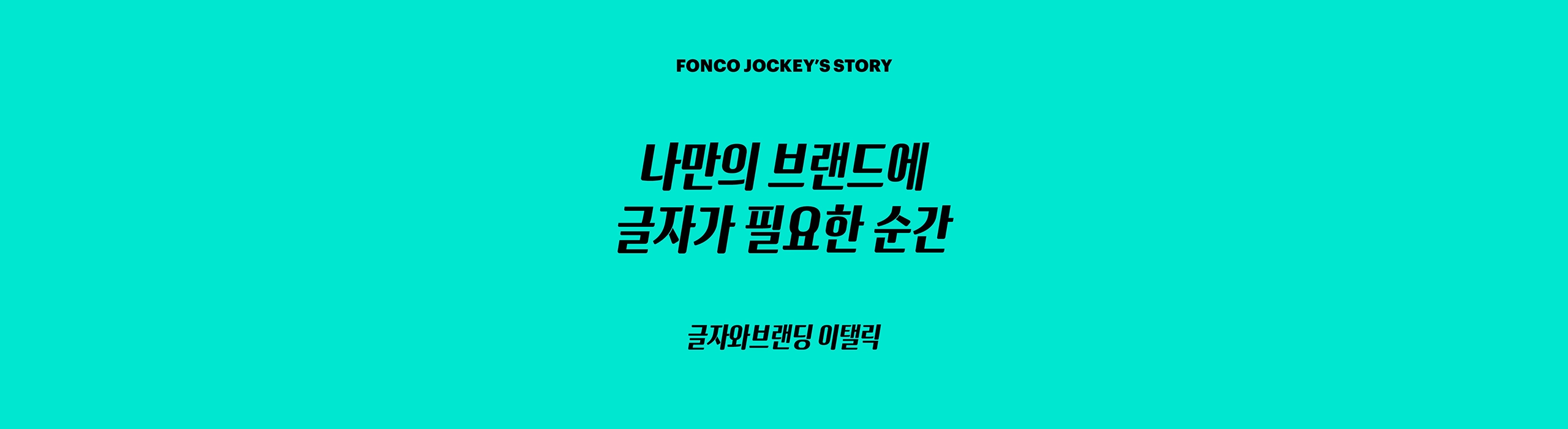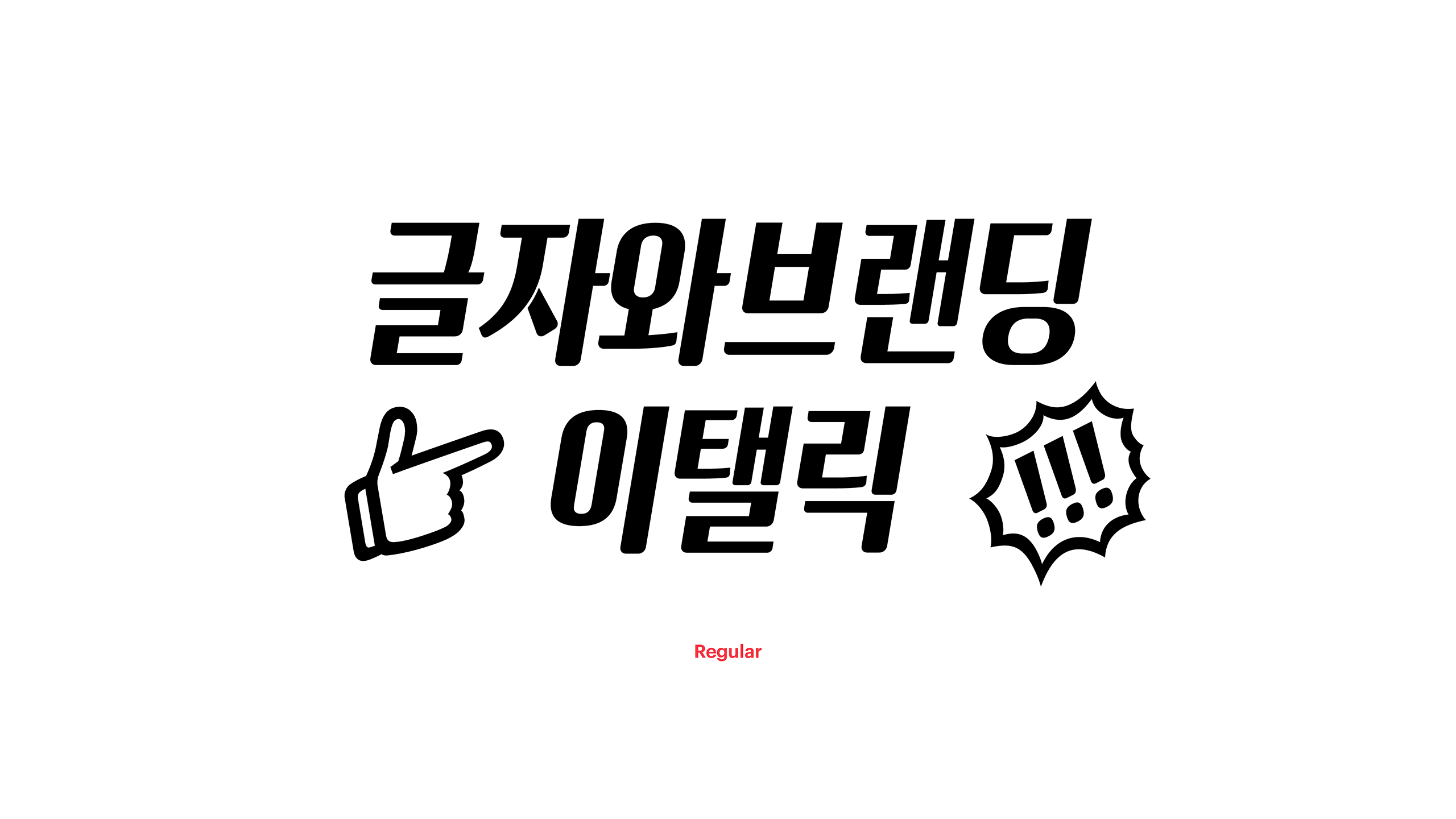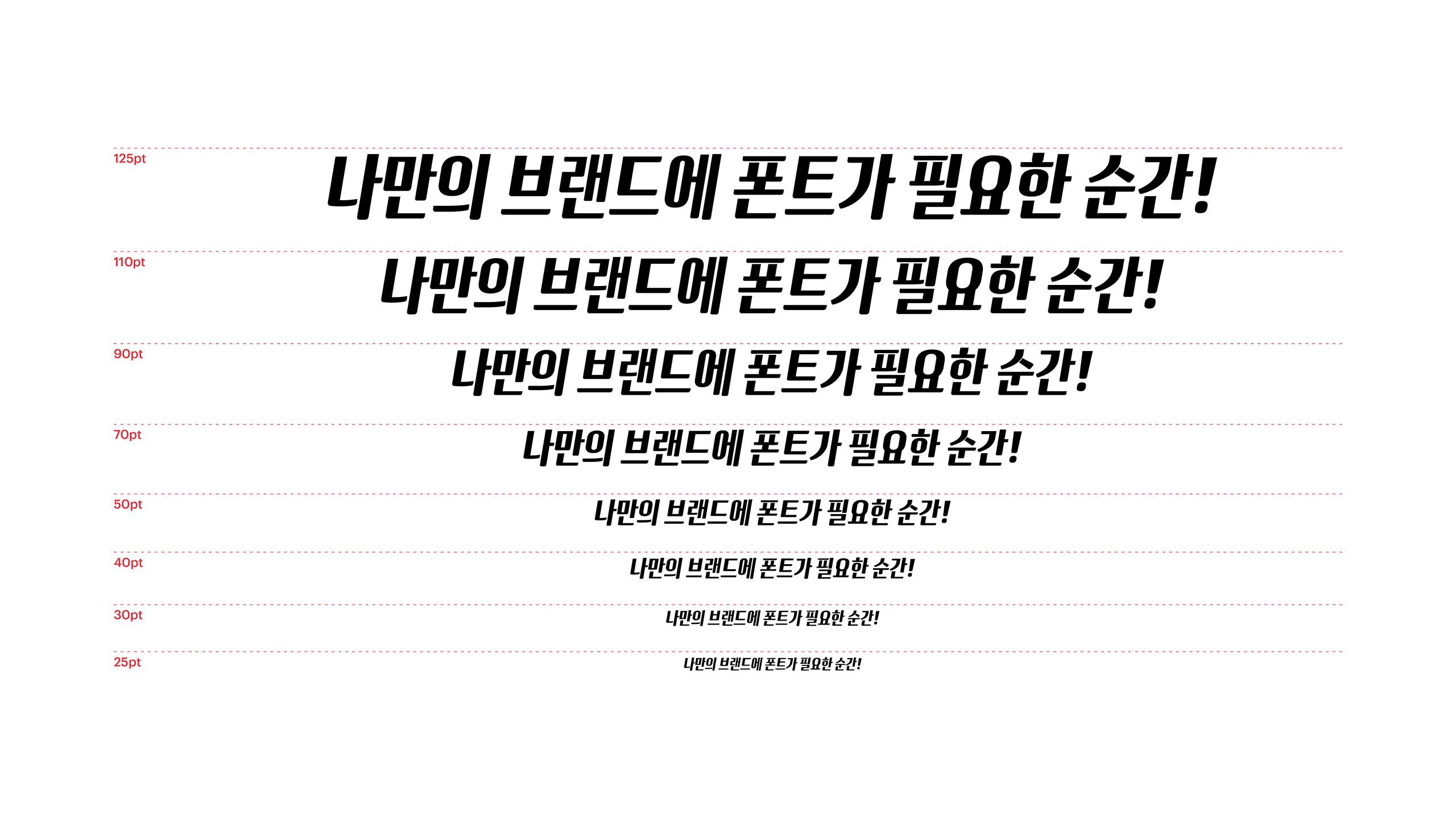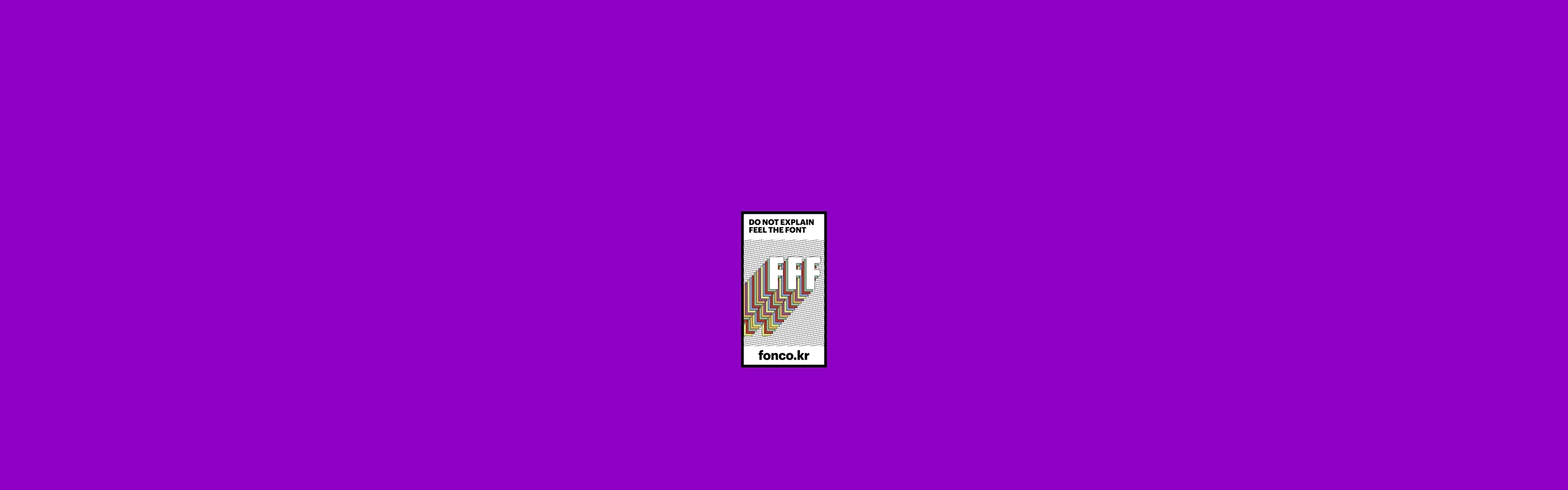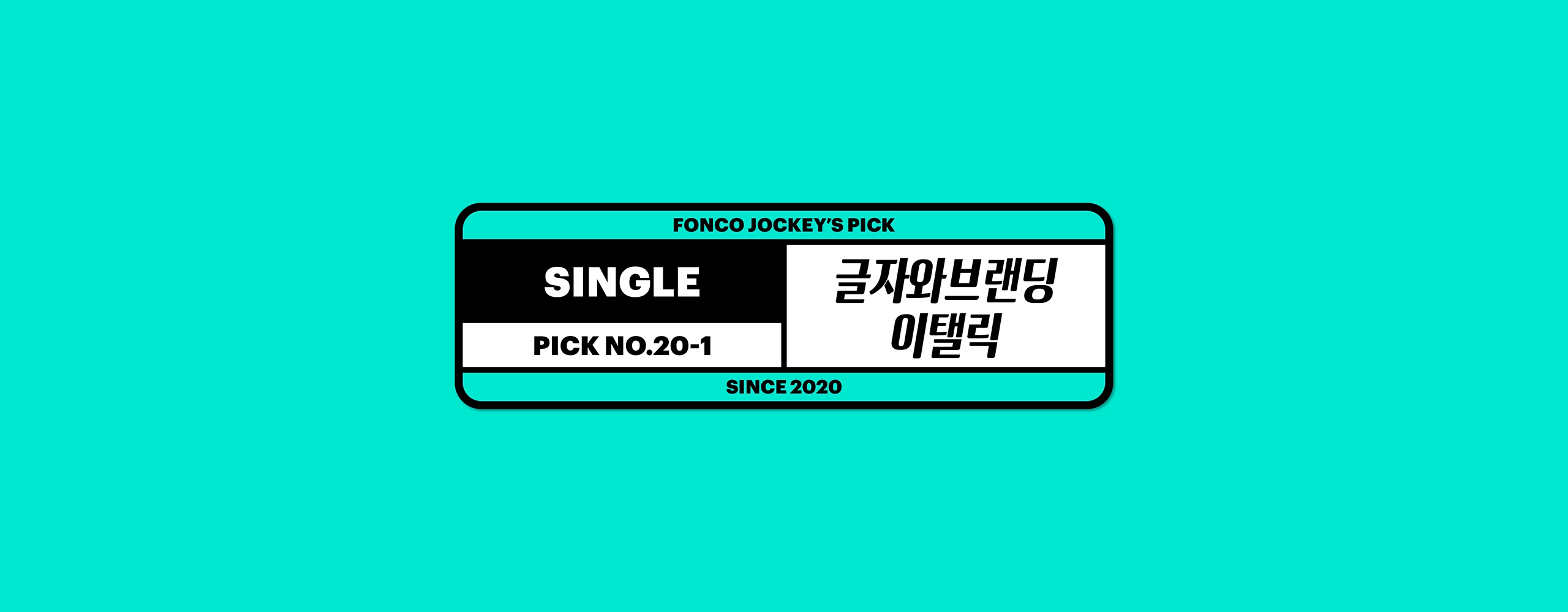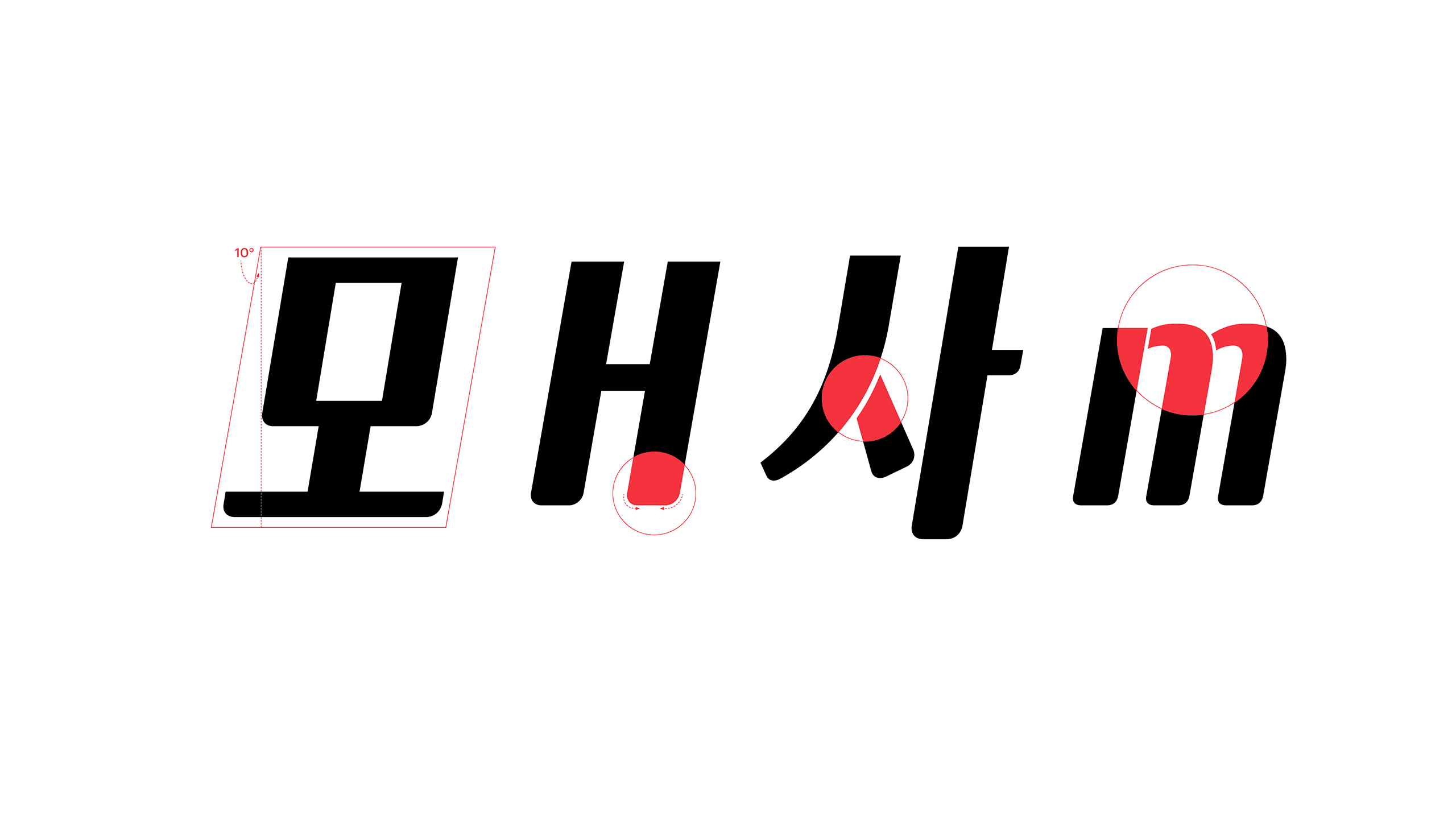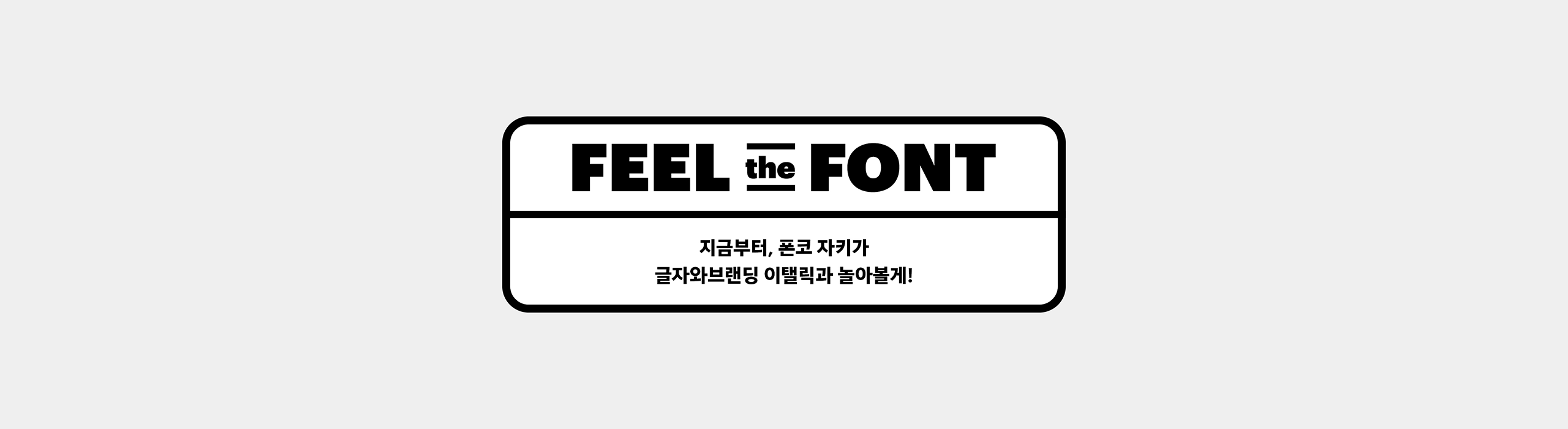
글자와브랜딩이탤릭은 나만의 브랜드에 글자가 필요한 순간, 유용한 쓰임을 고려하여 제작한 폰트입니다. 아무리 크게 써도 세련미를 잃지 않는 요 폰트 하나만 있다면 옥외 간판도 시즌별 광고도, 나만의 로고와 명함, 메뉴판까지도. 뚝딱뚝딱 손쉽게 만들어낼 수가 있다구요.
글자와브랜딩 이탤릭체는 나만의 브랜드를 꿈꾸는소상공인을 위해 제작한 폰트입니다.폰트 하나만으로 나만의 가게나 스튜디오 브랜딩을 시작할 수 있지요.옥외간판, 메뉴판, 간단한 로고타입이나 명함 등브랜딩의 A to Z를 경험할 수 있도록도와주는 갓(God)성비 폰트를 만나보세요.